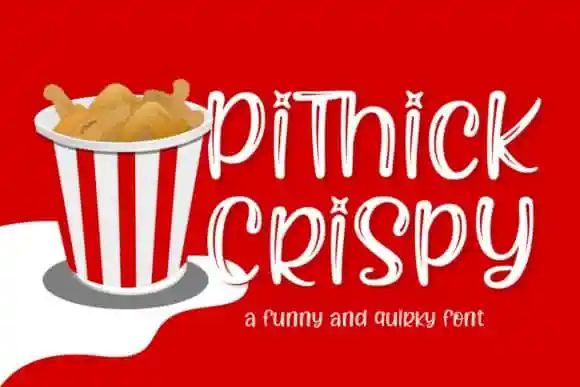
A Pithick Crispy Display Font é uma beleza em letras maiúsculas perfeita para ocasiões relacionadas a crianças. Esta fonte foi projetada e compartilhada pelo Ghuroba Studio, oferecendo uma opção charmosa e acolhedora para trabalhos de design que buscam destaque. A Pithick Crispy é um tipo de exibição leve e descontraída, perfeitamente adaptável a diversas demandas de projeto, desde identidades de marca até assinaturas, logotipos e rótulos, garantindo sempre um toque jovial em qualquer trabalho que ela padece. Não perca essa fonte única para dar ao seu design uma cara jovial e descolada.